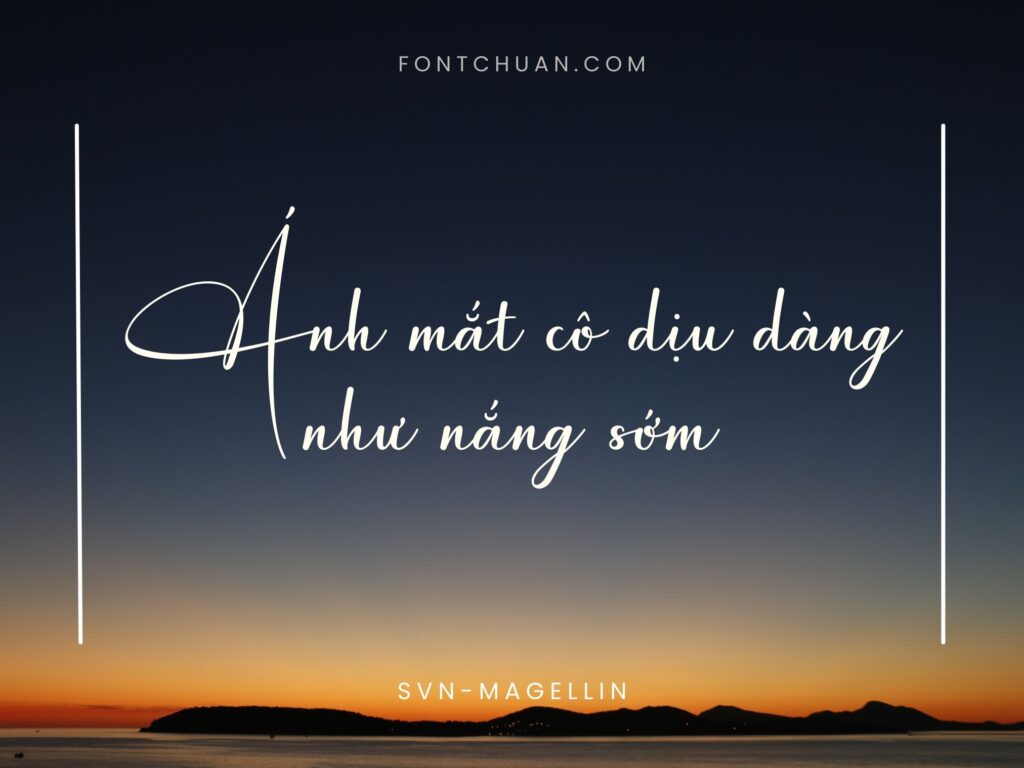
Font SVN Magllin Việt Hóa
Font SVN Magellin là phiên bản Việt hóa của kiểu chữ Magellin, được thực hiện bởi STYLEno.1 Fonts. Magellin là một kiểu chữ ký thanh lịch, mang đến sự tinh tế và phong cách cho các thiết kế của bạn. Với đặc trưng gần gũi của Font chữ viết tay, Magellin giúp tạo nên cảm giác tự nhiên và giàu cảm xúc trong từng thiết kế. Font này bao gồm các chữ cái kết nối và một số ký tự thay thế, phù hợp cho nhiều dự án như tài liệu thương hiệu, áo thun, in ấn, danh thiếp, logo, poster, nhiếp ảnh, trích dẫn và nhiều hơn nữa. Magellin hỗ trợ đa ngôn ngữ và chứa các ký tự chữ hoa, chữ thường, chữ số và dấu câu, mang lại sự linh hoạt cao trong sáng tạo.
Đặc biệt, khi được ứng dụng trong các dự án hiện đại, Magellin có thể ứng dụng làm Font chữ công nghệ để vừa giữ nét sang trọng, mềm mại, vừa thể hiện được tính hiện đại và chuyên nghiệp. Nhờ đó, các thiết kế logo, thương hiệu hay bao bì sản phẩm dễ dàng tạo dấu ấn mạnh mẽ và khác biệt.
SVN Magellin phù hợp cho các thiết kế như logo thương hiệu, tiêu đề, bao bì sản phẩm và các ấn phẩm truyền thông. Các ngành nghề như quảng cáo, giáo dục và công nghệ có thể tận dụng font này để tạo điểm nhấn trong thiết kế. Ngoài ra, font cũng thích hợp cho các sự kiện như Tết, Giáng sinh, Valentine và các lễ hội khác.